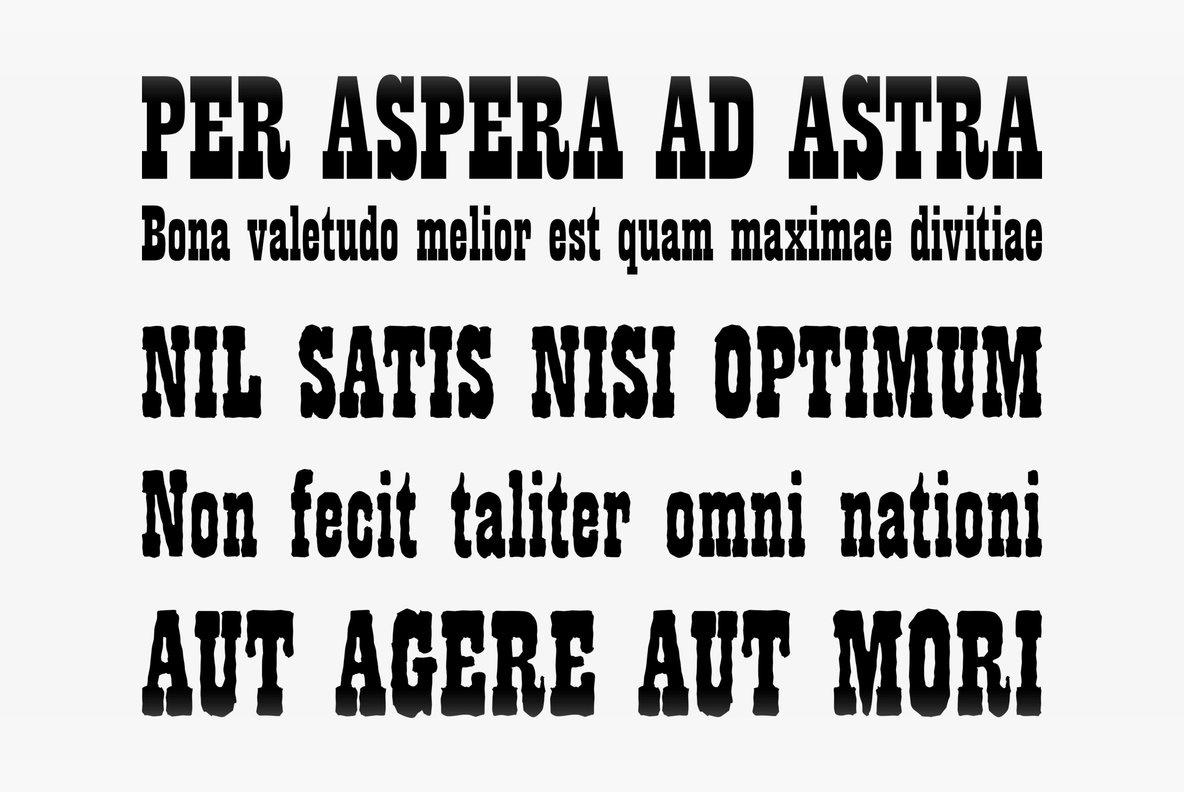
Playbill Font
Description de Playbill Font
Playbill est une police slab serif qui a gravé sa place dans l’architecture typographique grâce à son visage robuste et persistant. Conçue par Robert Harling en 1938, cette police symbolise la force et l’expressivité et reste un choix privilégié pour les titres, les affiches et les annonces théâtrales.
Spécifique à ses empattements carrés robustes et à ses formes de lettres soignées, Playbill respire le drame et le frisson. Chaque lettre est conçue avec soin pour briller, captiver l’attention et exprimer la vivacité de l’événement. En fusionnant les éléments du design de Pierpont avec des commodités modernes, Harling peut préserver l’esprit du Playbill original.
La caractéristique déterminante de Playbill est sa condensation, qui a un impact maximal sur une petite zone. Cette condensation lui donne son aspect distingué et le rend donc idéal pour transmettre la nature dramatique de l’impression. Les traits solides et les empattements nets de Playbill garantissent sa lisibilité même dans les grandes tailles, ce qui en fait une police polyvalente aussi bien pour le numérique que pour l’impression.
Bien qu’il ait commencé comme un outil utilisé dans des programmes théâtraux, Playbill est devenu plus que cela et a trouvé des applications dans diverses applications de conception. Sa nature expressive et audacieuse en fait un excellent choix pour le branding, la publicité et la conception éditoriale, où il peut injecter de la couleur et du mouvement dans les projets.
Alors que les designers recréent et améliorent les Playbills classiques, le public est distrait par la magnificence de Broadway et l’excitation des spectacles en direct. La popularité durable et l’adaptabilité ont toujours assuré à la calligraphie une place dans l’arsenal du designer ; par conséquent, il ne cessera d’avoir un impact sur la scène du design.